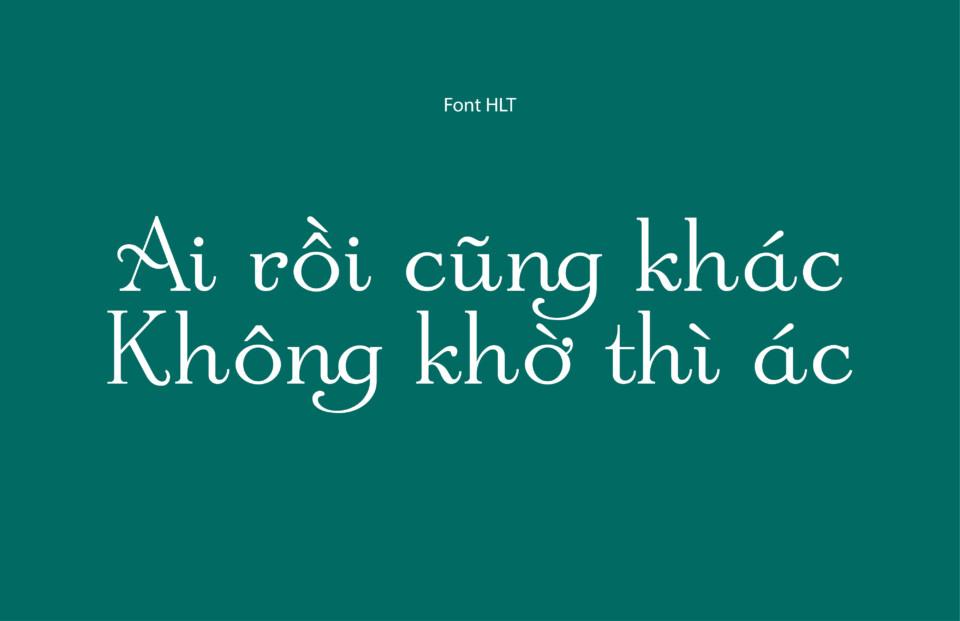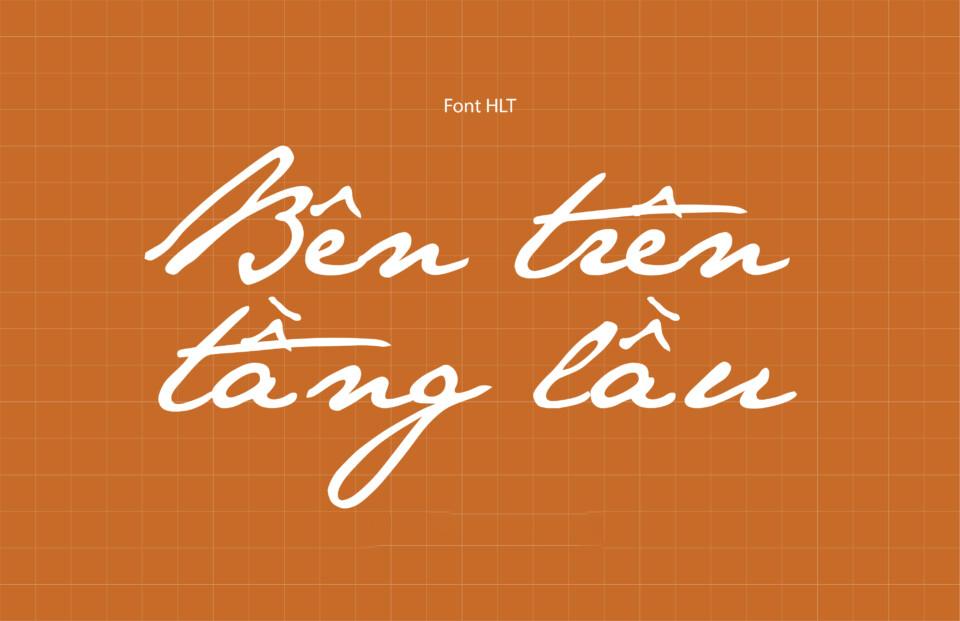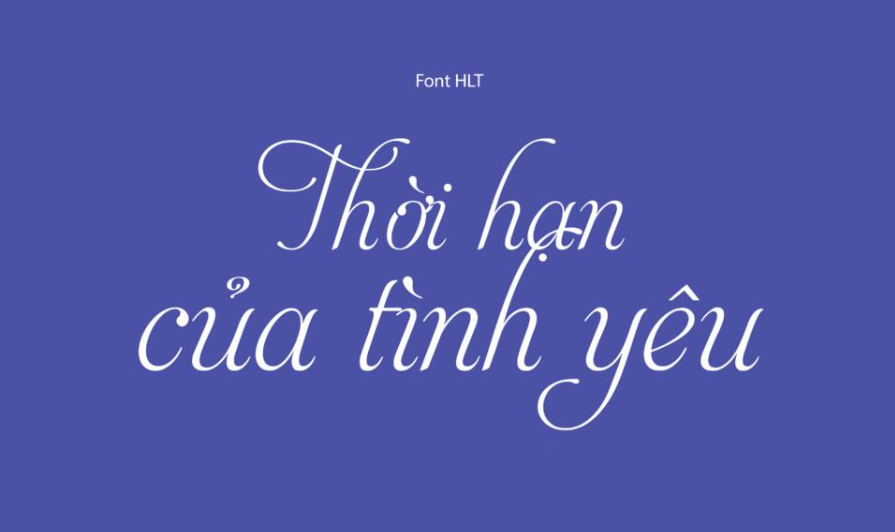
Hệ thống font HLT Việt hóa từ lâu đã trở thành kho tài nguyên quen thuộc đối với những người làm nghề thiết kế đồ họa và kỹ thuật tại Việt Nam. Với khả năng hỗ trợ bảng mã Unicode chuẩn và sự đa dạng trong phong cách, bộ phông chữ này giúp các Kiến trúc sư trình bày hồ sơ dự án, bản vẽ phối cảnh hay bộ nhận diện thương hiệu một cách đồng bộ và chuyên nghiệp.
Khám phá những ưu điểm của dòng font HLT Việt hóa trong thiết kế
Điểm lôi cuốn của bộ font HLT Việt hóa chính là sự tỉ mỉ trong việc xử lý các dấu thanh tiếng Việt, giúp văn bản duy trì được nhịp điệu hình học và cấu trúc cân đối của bộ chữ gốc. Khác với những phông chữ chưa được tối ưu, phông chữ HLT loại bỏ hoàn toàn các lỗi nhảy chữ hay sai khoảng cách dấu, mang lại sự mạch lạc cho các bản thuyết minh dự án hay ghi chú trên bản vẽ.
Sự chuyên nghiệp của dòng phông này còn nằm ở khả năng hiển thị tương thích trên nhiều nền tảng. Dù bạn sử dụng để trình bày trên màn hình kỹ thuật số hay in ấn trực tiếp trên các vật liệu xây dựng thực tế như tấm panel, mica gương hay inox, các đường nét vẫn giữ được độ sắc sảo và rõ ràng. Đây là giải pháp phù hợp để thể hiện tư duy thiết kế khoa học, giúp truyền tải thông điệp về sự chỉn chu và năng lực chuyên môn của đơn vị thi công đối với khách hàng và đối tác.
| Phân loại phong cách | Sans-serif / Serif / Modern Style |
| Số lượng kiểu chữ | Đa dạng nhiều biến thể phông chữ phổ biến |
| Mục đích phù hợp | Bản vẽ kỹ thuật, Profile dự án, Website kiến trúc |
Gợi ý trình bày: Để bản thiết kế đạt được hiệu quả thị giác tốt, bạn nên sử dụng các dòng phông HLT không chân (Sans-serif) cho phần nội dung mô tả chi tiết nhờ độ thông thoáng cao. Đối với các đề mục lớn hoặc tiêu đề trang bìa hồ sơ, hãy phối hợp cùng một biến thể đậm để tạo ra sự phân cấp thông tin rõ ràng và chuyên nghiệp.
03 Ứng dụng phông chữ HLT vào thực tế công trình
Nhờ diện mạo khoa học và giàu tính thực dụng, việc sử dụng các kiểu chữ từ tải font HLT Việt hóa mang lại giá trị thực tế lớn trong khâu quản lý và quảng bá các dự án xây dựng:
- Ghi chú thông số trên bản vẽ AutoCAD: Độ rõ nét của các dòng phông kỹ thuật trong bộ HLT hỗ trợ đắc lực cho kỹ sư khi trình bày các chú thích vật liệu panel, kích thước dầm thép, giúp đội ngũ giám sát thi công tại hiện trường tra cứu thông tin chính xác.
- Hệ thống nhận diện cho homestay và văn phòng: Những nét chữ hiện đại của phông chữ HLT rất ăn ý khi gia công cắt nổi trên vật liệu alu hoặc mica. Kiểu chữ này giúp không gian toát lên vẻ chỉn chu, chuyên nghiệp và tạo sự tin cậy đối với khách hàng.
- Thiết kế hồ sơ năng lực: Sử dụng bộ font HLT Việt hóa giúp trình bày thông tin năng lực thi công một cách mạch lạc trên các khổ giấy A4, tạo ấn tượng về một đơn vị thi công có quy trình làm việc bài bản và tư duy thẩm mỹ hiện đại.
03 Lưu ý để bố cục phông chữ HLT đạt độ sắc nét cao
Để khai thác hiệu quả vẻ đẹp trung tính của dòng phông đa năng này mà không làm rối mắt người xem, người thiết kế nên lưu tâm một số kinh nghiệm sau:
- Kiểm soát khoảng cách dòng: Với cấu trúc chữ hiện đại của HLT, bạn nên thiết lập khoảng cách dòng thoáng một chút (khoảng 1.3 – 1.5 lần cỡ chữ) để văn bản không bị bết dính, giúp người đọc cảm thấy thư giãn khi tiếp nhận nội dung thuyết minh dự án dài.
- Sử dụng biến thể Bold làm điểm nhấn: Hãy tận dụng các biến thể đậm của font HLT Việt hóa cho các con số hoặc hạng mục quan trọng trong dự toán công trình để tạo độ nhấn thị giác mạnh mà không cần sử dụng quá nhiều màu sắc gây nhiễu.
- Kiểm tra hiển thị trên thiết bị di động: Nếu dùng cho nội dung số, hãy kiểm tra khả năng hiển thị của phông chữ trên màn hình điện thoại để chắc chắn các dấu thanh tiếng Việt không bị quá nhỏ hoặc khó nhận diện đối với khách hàng.